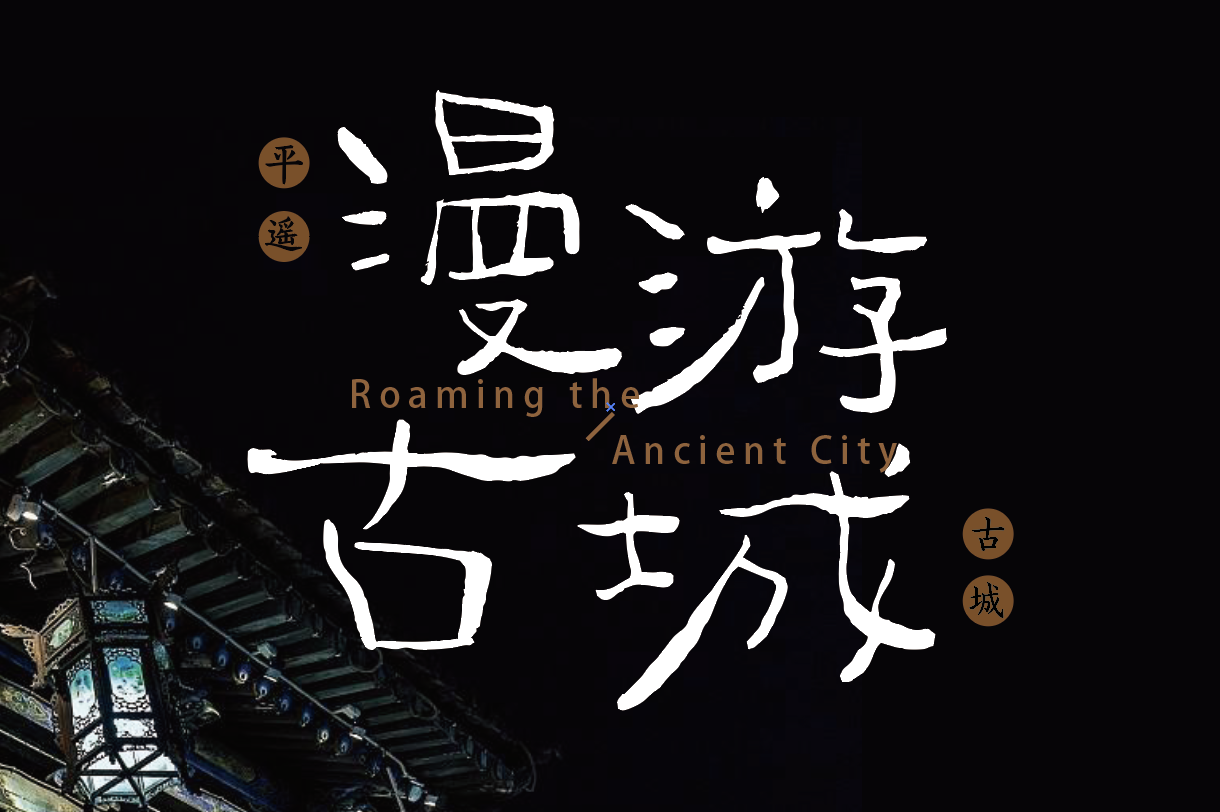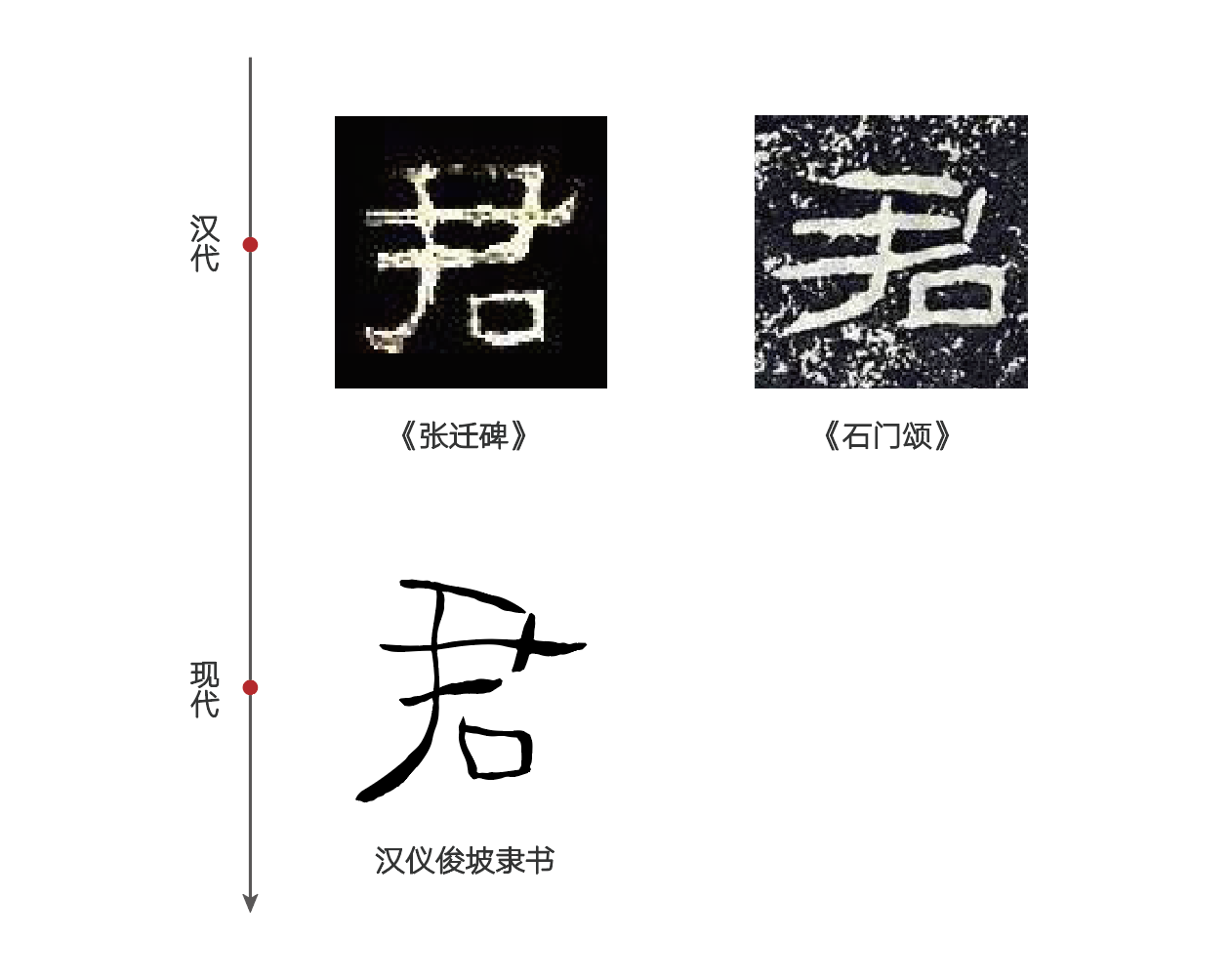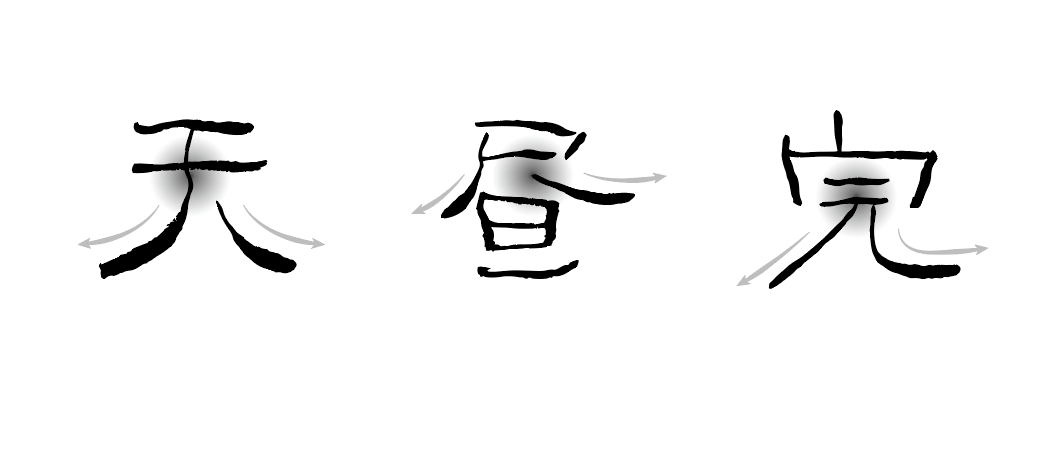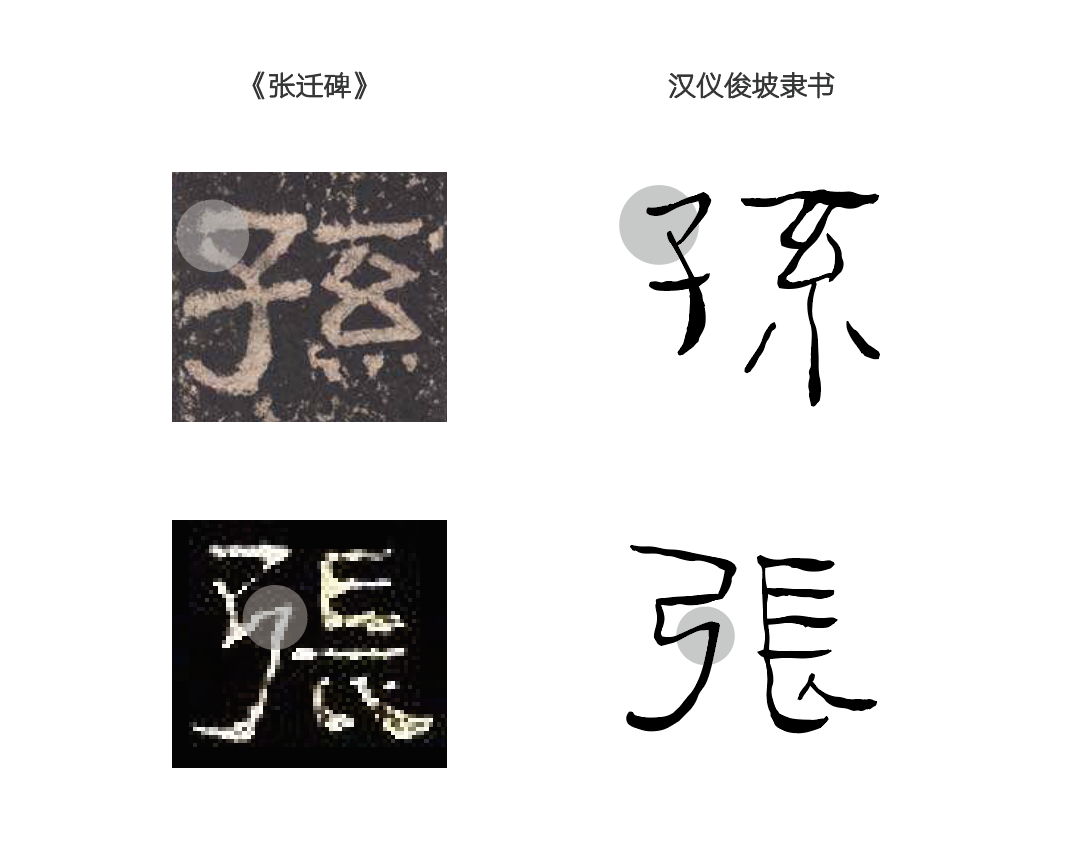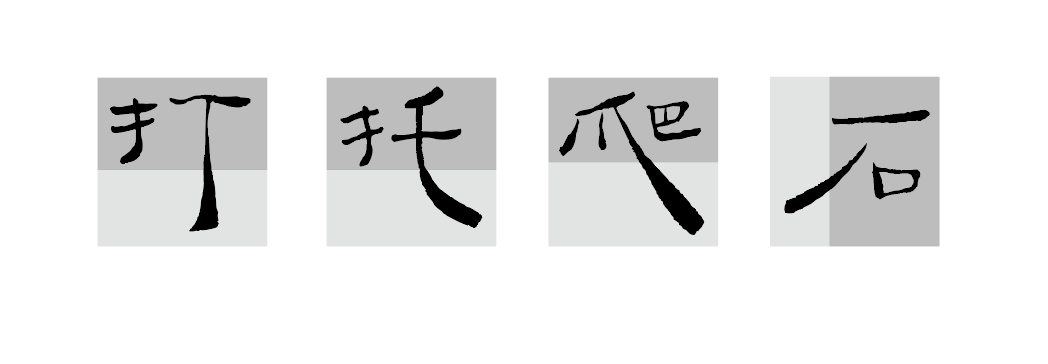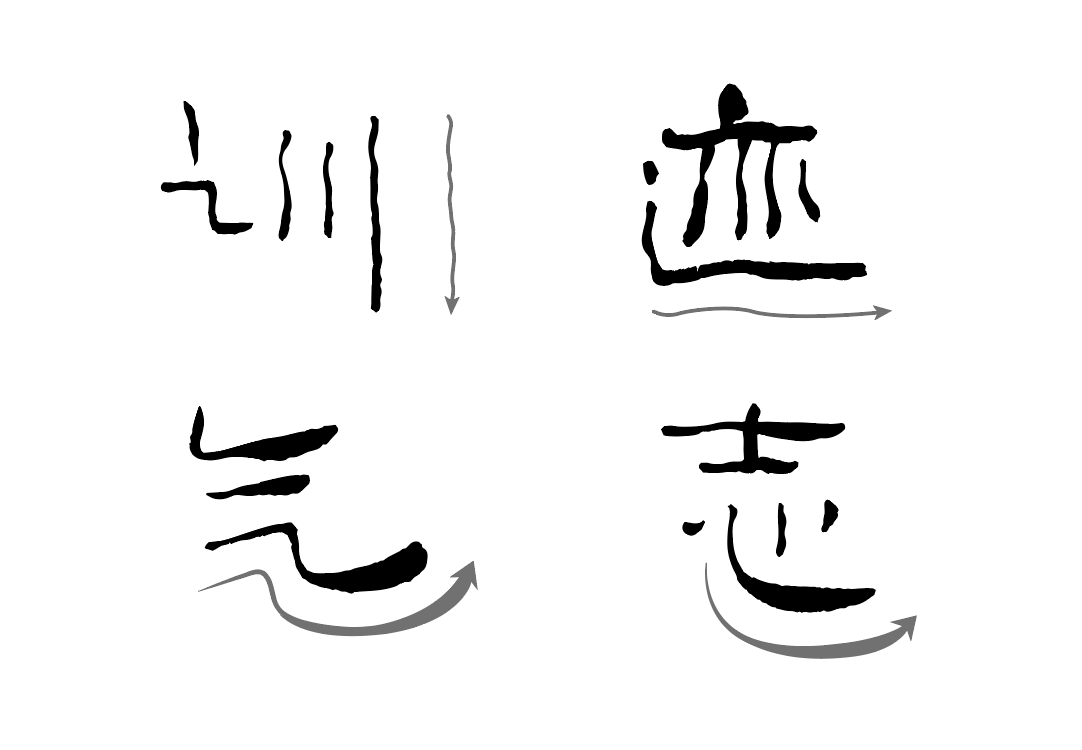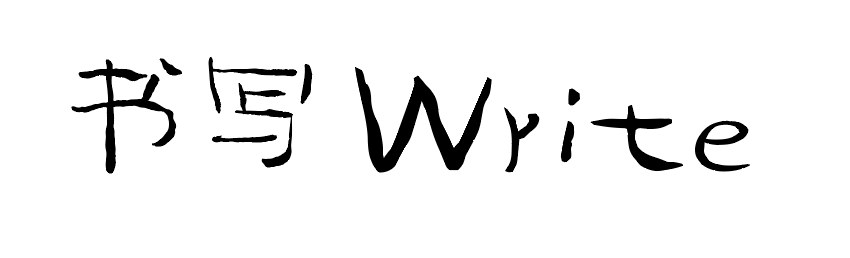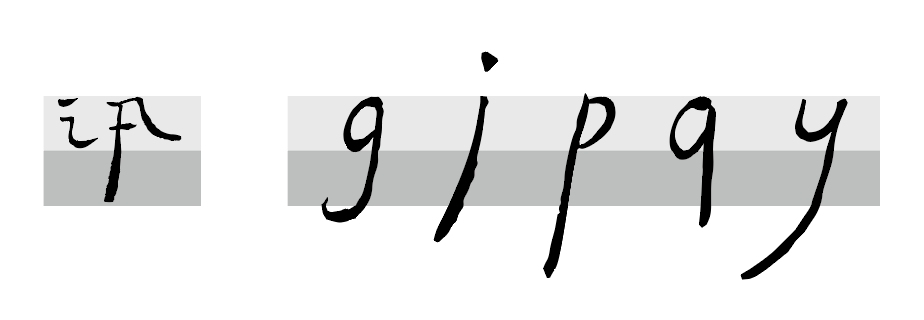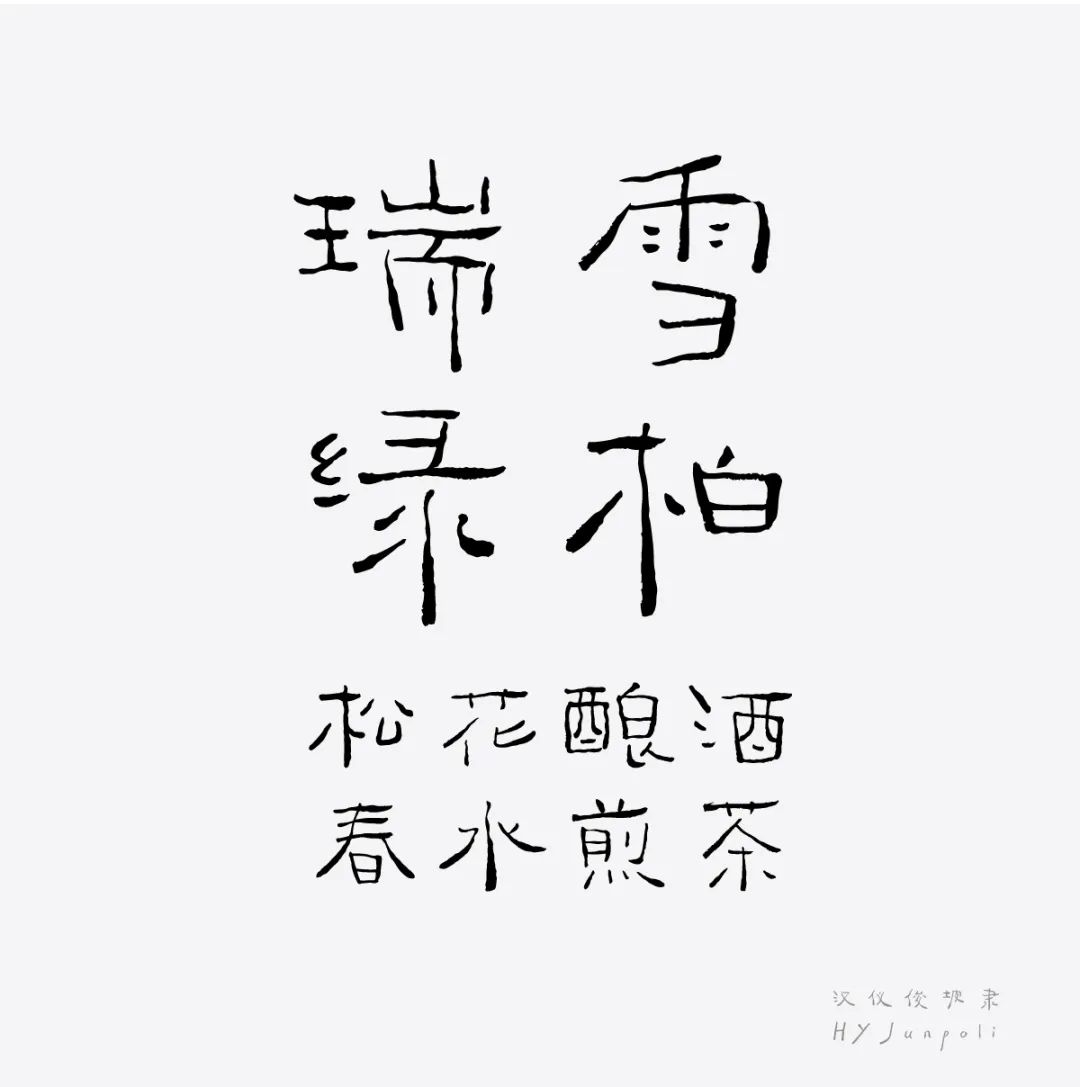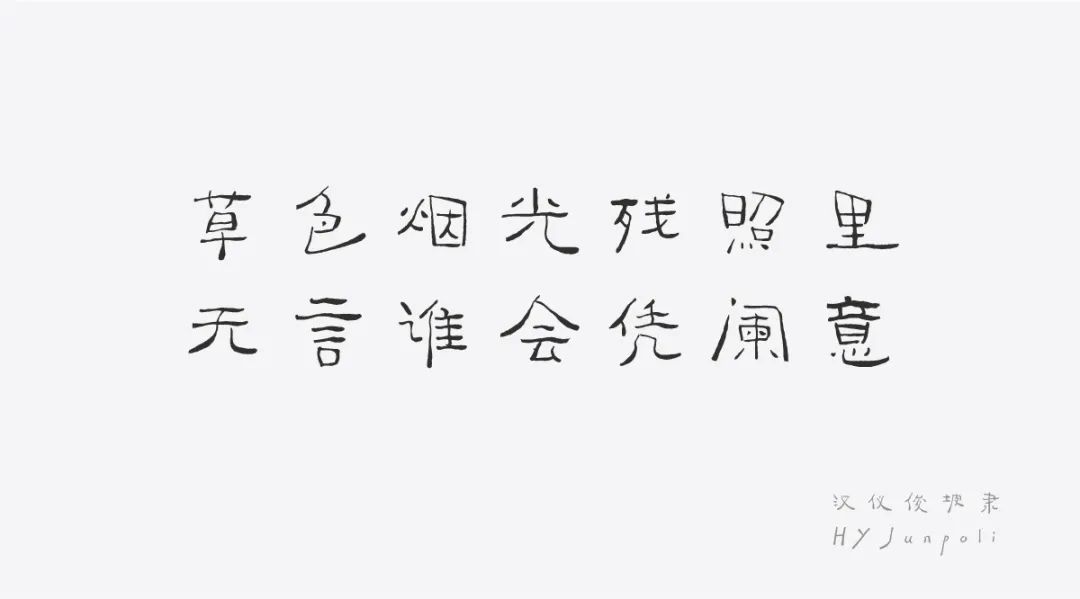
字体名称: 汉仪俊坡隶W
汉仪俊坡隶W
汉仪俊坡隶W介绍
“汉仪俊坡隶书”是一款带有浓郁古拙意味的隶书作品。它是由著名的简牍书法家刘俊坡倾力书写创作而成。“汉仪俊坡隶书”的诞生,不仅重新唤醒了简牍背后的民族记忆,更阐释传承一个民族的光荣与梦想。
“汉仪俊坡隶书”以汉代《张迁碑》和《石门颂》结体为构字基础,形成书风端正朴茂、结体巧妙大方,既有汉代庙堂遗韵,又含现代汉字审美的浪漫气息。
“汉仪俊坡隶书”以简牍墨迹的蝌蚪法和玉箸法为书写造型元素,字体内敛外放,典雅自然,有着含蓄蕴藉的审美情趣。
“汉仪俊坡隶书”的写法参考和保留了《张迁碑》的处理方式,还原了字体简单淳朴的韵味。
汉仪俊坡隶书 | 笔画特点
“汉仪俊坡隶书”笔画拖长似飘带状,字体显得灵动飘逸,结构疏密对比明显。这样的处理方式,打破了字体在演变过程中的僵化与呆板,赋予字体以灵性。
“汉仪俊坡隶书”笔画提按过渡明显,线条灵动活泼,粗细相间,赋予字体强烈的画面感,整体效果显得沉雄厚重。
汉仪俊坡隶书 | 中西文匹配
“汉仪俊坡隶书”西文字母充分吸收了中文结构,笔画和线条的特点,形成了带有古拙韵味的字母。中、西文搭配使用时呈现出更佳的视觉效果。
“汉仪俊坡隶书”西文字母提取了中文字体笔画的部分处理方式。降低了字母下缘线的位置,拉长了笔画结构。
汉仪俊坡隶书 | 字体展示